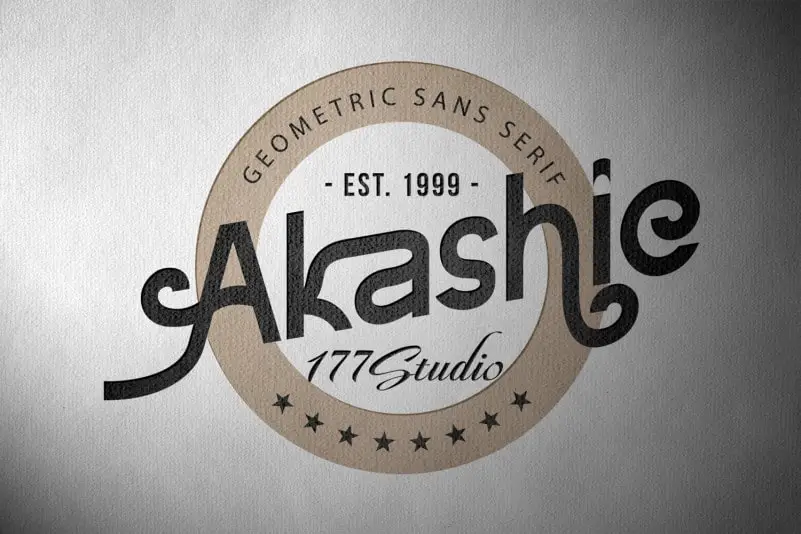
Akashic Font – Fonte Grátis
Akashic Font
Akashic Font é uma elegante tipografia sans serif que se destaca com sua mistura moderna e sofisticaada. Embora seja um tipo clássico, a fonte ganha frescura através de seu toque contemporâneo, o que torna-a perfeita para qualquer projeto que exija simplicidade e elegância. Além disso, Akashic Font inclui algumas gílias adicionais e ligaturas, garantindo uma versatilidade incrível para complementar projetos diversos como cartões de casamento, t-shirts ou outros elementos gráficos. Seu estilo sofisticado e moderno a torna um recurso indispensável para designers buscando adicionar um toque único aos seus trabalhos.